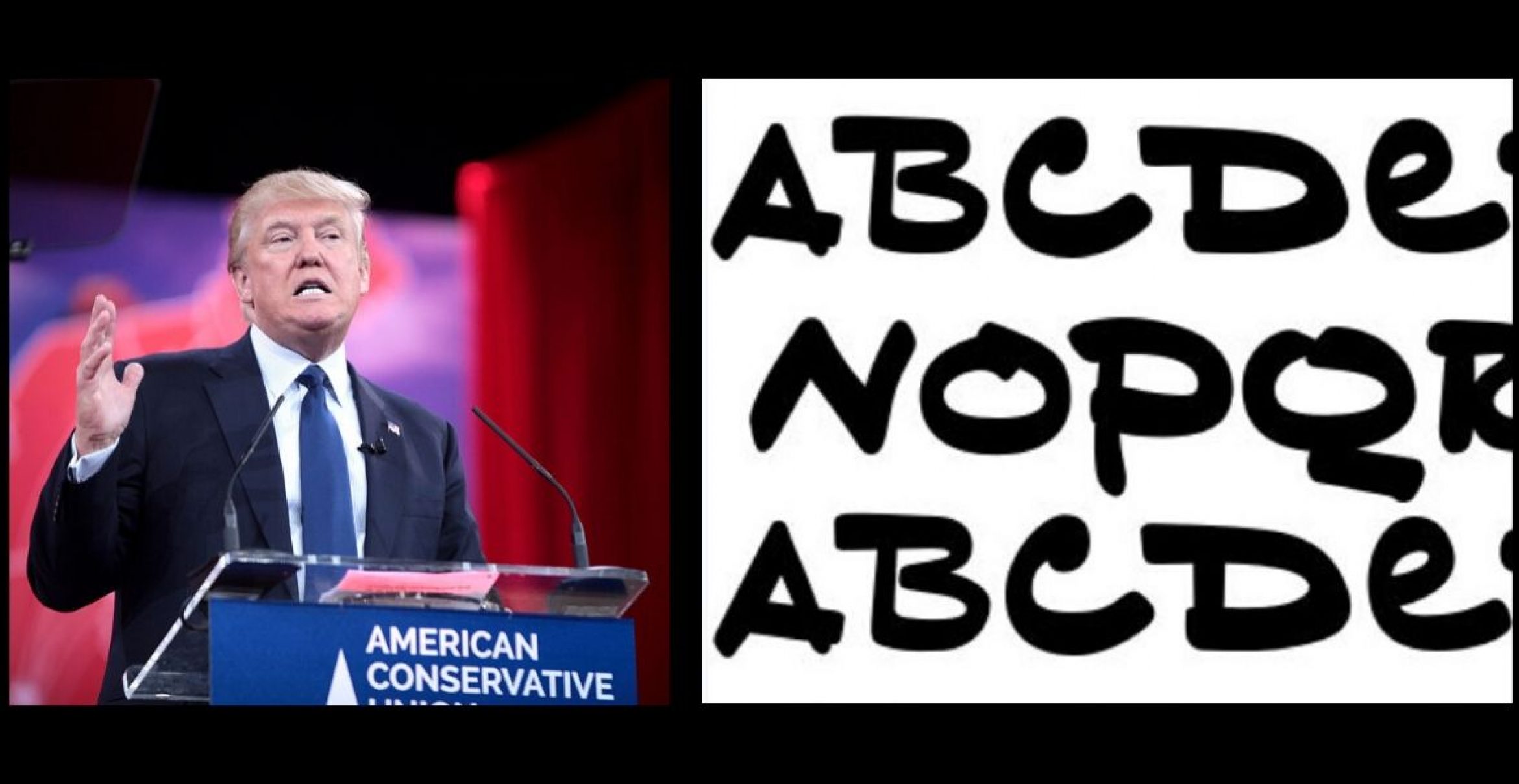
Diese Trump-Font eignet sich perfekt für passiv-aggressive Zettel im Büro
Seit langem ist Comic Sans die meist verspottete Schriftart, die Word zu bieten hat. Das könnte nun ein Ende haben. Denn: Mark Davis, Grafikdesigner bei „Buzzfeed“, hat die Font „Tiny Hand“ ins World Wide Web gebracht. Wer viel in der Meme-Kultur unterwegs ist, weiß bereits, auf wen sich die Schriftart bezieht, nämlich auf Donald Trump.
Erst diese Woche hat ein Pressefotograf Trumps Notizzettel abfotografiert, als dieser eine Aussage zur Ukraine-Affäre gemacht hatte. Das Foto ging viral. Unter anderem aufgrund der Handschrift des Präsidenten, die in runden Großbuchstaben daher kommt. Was sollen wir sagen? Davis‘ Variante ist ziemlich gut gelungen, oder?